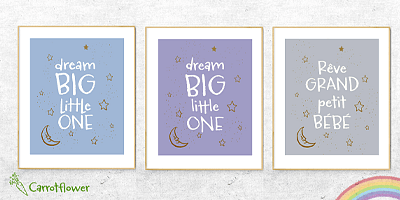
Đặc điểm thẩm mỹ độc đáo của bộ font SVN Carrotflower
Carrotflower không đi theo sự cứng nhắc của các phông chữ hình học; nó chinh phục người xem nhờ sự vụng về có chủ đích, gợi nhắc đến những nét vẽ nguệch ngoạc đáng yêu trong cuốn sổ tay tuổi thơ.
Phong cách viết tay ngộ nghĩnh và mộc mạc
Đặc trưng lớn nhất của SVN Carrotflower là các con chữ có kích thước và độ nghiêng biến thiên tự nhiên, không theo một đường thẳng cố định. Nét chữ thanh mảnh nhưng rõ ràng, các góc nối nét hơi bo cong nhẹ tạo cảm giác ấm áp và gần gũi. Khi đặt Carrotflower làm tiêu đề trên bao bì, thương hiệu của bạn sẽ ngay lập tức lan tỏa năng lượng tích cực, tạo cảm giác về một sản phẩm an toàn, lành tính và được làm bằng tất cả sự chăm chút yêu thương.
Nhịp điệu chữ nhảy múa tự nhiên và giàu năng lượng
Các ký tự của font SVN Carrotflower Việt hóa sở hữu đường chân chữ (baseline) nhấp nhô sống động, mô phỏng chân thực nhịp điệu của nét chữ viết tay ngẫu hứng. Phong cách này mang lại sự tươi vui, giải phóng bản thiết kế khỏi sự khô khan, cực kỳ ăn ý với các dòng sản phẩm bánh kẹo handmade, trà hoa quả sấy hoặc thời trang trẻ em tươi sáng.
03 Ưu điểm nổi bật của bản font SVN Carrotflower Việt hóa
Khi ứng dụng các phông chữ viết tay vào thị trường trong nước, sự chỉn chu về dấu câu là yếu tố quyết định đến tính chuyên nghiệp của bản thiết kế:
- Khắc phục triệt để lỗi dấu tiếng Việt: Phiên bản Việt hóa của SVN Carrotflower đã được đội ngũ thiết kế trau chuốt thủ công từng dấu câu. Các dấu sắc, huyền, hỏi, ngã, nặng được vẽ với phong cách mộc mạc đồng điệu cùng thân chữ gốc, không gây cảm giác chắp vá hay đè nét làm mất tính thẩm mỹ.
- Kiểm soát khoảng cách dòng (Leading): Do các ký tự của Carrotflower có độ cao nhấp nhô không đều, bạn nên căn chỉnh khoảng cách giữa các dòng chữ thủ công để tránh tình trạng các dấu thanh của dòng dưới chạm vào chân chữ của dòng trên.